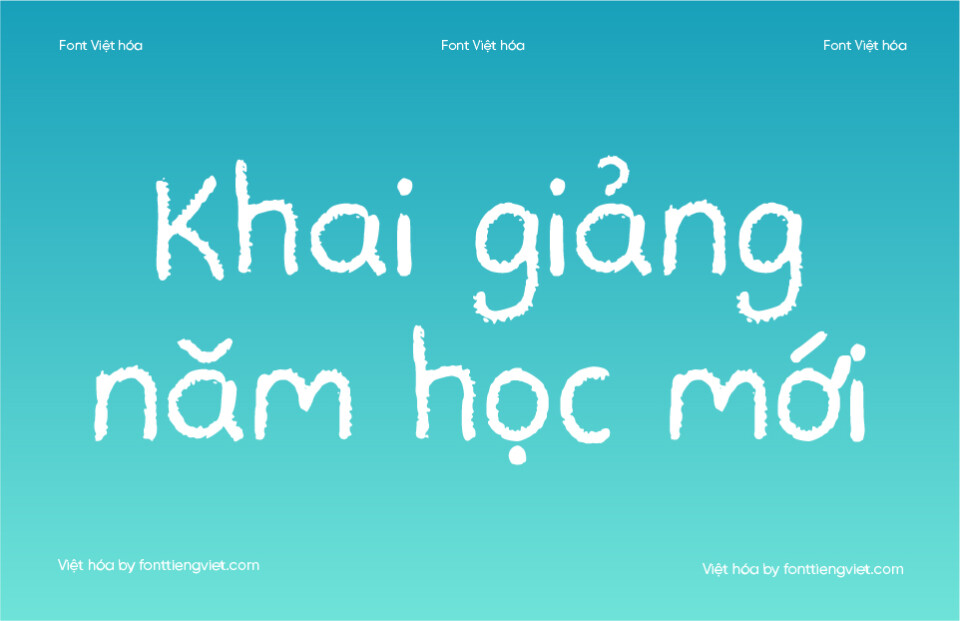
Giới thiệu về Font Việt hóa 1FTV VIP Teachers Student – Phấn
Trong môi trường giáo dục hiện đại, việc trình bày bài giảng sinh động đóng vai trò quan trọng trong việc thu hút sự chú ý của học sinh. Font Chữ đóng vai trò là cầu nối truyền tải tri thức một cách trực quan và gần gũi nhất. Font Việt hóa 1FTV VIP Teachers Student – Phấn là một bộ font đặc biệt được thiết kế mô phỏng nét viết phấn trên bảng đen, mang lại cảm giác thân thuộc của lớp học truyền thống. Với các đường nét thanh mảnh nhưng rõ ràng, bộ font này giúp các thầy cô tạo ra những bài giảng điện tử hoặc tài liệu học tập vô cùng ấn tượng và sáng tạo.
Đặc điểm nổi bật của Font Việt hóa 1FTV VIP Teachers Student – Phấn
Bộ font này đã được tối ưu hóa hoàn toàn cho bảng mã Unicode, giúp người dùng gõ tiếng Việt một cách mượt mà mà không lo lỗi font. Điểm cộng lớn nhất của Font Việt hóa 1FTV VIP Teachers Student – Phấn chính là sự tỉ mỉ trong từng nét vẽ, tái hiện chân thực hiệu ứng bụi phấn rơi trên mặt bảng. Đây là lựa chọn lý tưởng để thiết kế tiêu đề bài giảng, thiệp mời họp phụ huynh hoặc các bảng tin nội bộ trong nhà trường.
Cách ứng dụng Font Việt hóa 1FTV VIP Teachers Student – Phấn hiệu quả
Để phát huy tối đa vẻ đẹp của bộ font này, người dùng nên kết hợp với các hình nền màu xanh đậm hoặc màu đen đặc trưng của bảng viết. Sử dụng các gam màu trắng, vàng nhạt hoặc xanh phấn sẽ tạo ra độ tương phản tốt, giúp học sinh dễ dàng theo dõi nội dung từ xa. Việc áp dụng Font Việt hóa 1FTV VIP Teachers Student – Phấn vào các slide thuyết trình PowerPoint không chỉ nâng cao tính thẩm mỹ mà còn khơi gợi cảm hứng học tập tích cực cho các em học sinh.